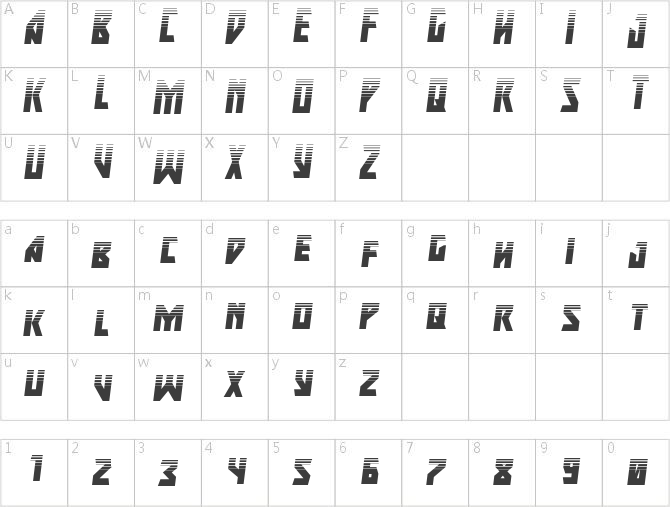
Major Force Halftone Italic 詳情頁
Major Force Halftone Italic字體字庫是一款讓人賞心悅目、百看不厭的英文字體,適合各類廣告和產(chǎn)品包裝設(shè)計應(yīng)用,字體大小0.03MB,格式為ttf字體,上傳用戶是洛洛,作者/版權(quán)方為未知